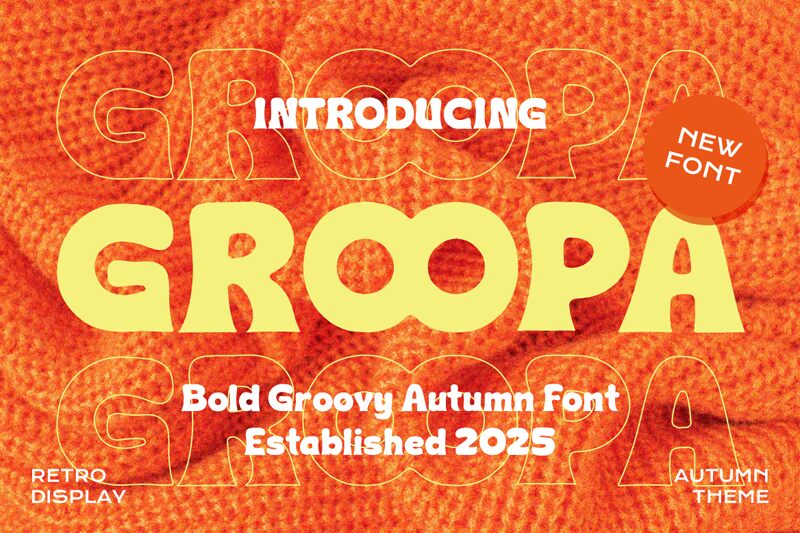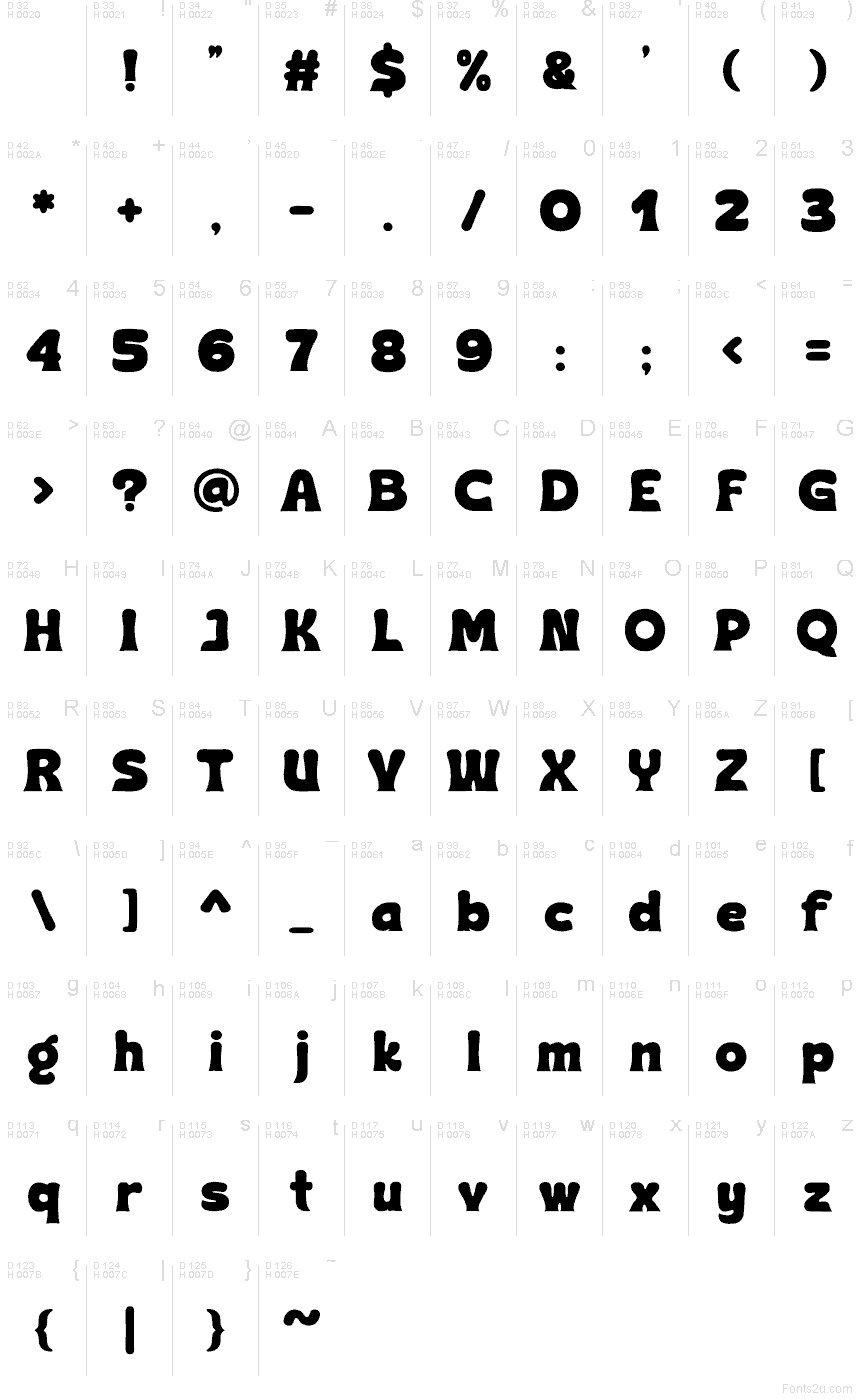
Groopa, realizzata dallo Shanaf Studio, è un font display gratuito dallo stile groovy che richiama la morbidezza degli anni '70. Le lettere appaiono gonfie e corpose, con curve massicce, giunzioni strette e un'oscillazione giocosa che conferisce al lettering un aspetto rilassato, anziché troppo levigato.
È perfetto per poster, flyer musicali, packaging, branding per bar e intestazioni sui social media dove un tocco retrò e amichevole aiuta a creare l'atmosfera giusta. Essendo un font gratuito, Groopa funziona molto bene anche per titoli brevi, copertine e bozze di loghi, poiché il suo ritmo morbido e le forme rotonde e pesanti catturano l'attenzione in poche lettere.